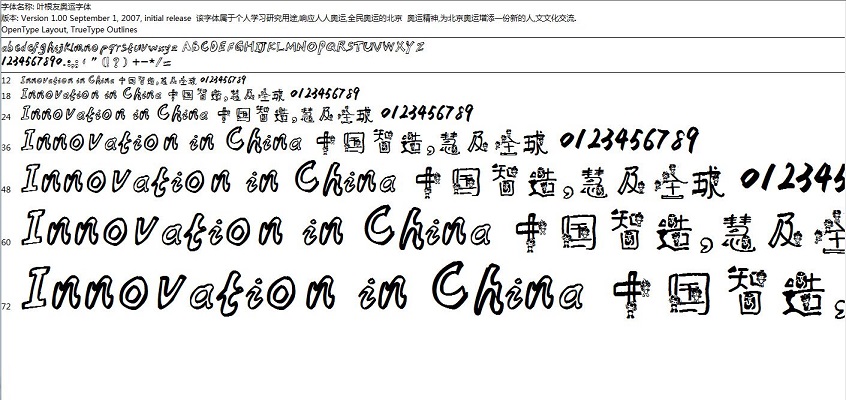
葉根友奧運字體是由葉根友先生特地為08北京奧運準備的一套書法字體,該字體結合了大量奧運特色創(chuàng)作而出,十分有象征意義,感興趣的朋友們快來下載吧!
在2007年8月8日距離奧運會倒計時一年之際,由著名書法家、連筆空心字吉尼斯紀錄保持者、五筆同書世界首創(chuàng)者葉根友先生親自書寫創(chuàng)作,中華簽名網和書體坊聯(lián)合開發(fā)的一套字體-《葉根友奧運字體紀念版》即每個中文漢字都有 “中國印·舞動的北京”或者“奧運五福娃-北京歡迎您”。其根據中國漢字的特點進行創(chuàng)作,如:點,就用“中國印·舞動的北京”來代替;底橫劃或者長橫以及豎劃和四點水就用奧運五福娃來代替。該款字體屬gb2312字體庫,共6763個漢字的標準字庫。